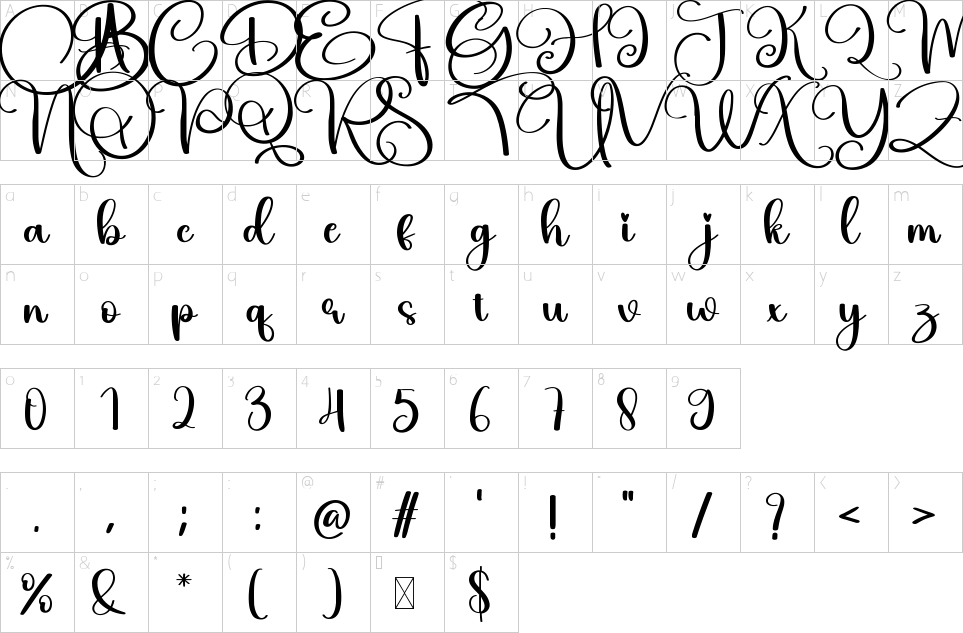
Anime Font é uma fonte animada e divertida, perfeita para aqueles que desejam dar um toque especial a seus projetos. Designada por scratchones, esta fonte foi projetada para aprimorar a experiência do design em ambientes Windows e Mac. Com uma aparência vibrante e animada, ela adicionará um toque especial e único aos textos em suas criações. Esta fonte já foi baixada 1,787 vezes, evidenciando o seu valor e popularidade entre criadores de design. Em uma categoria de fontes gratuitas, Anime Font não só oferece um design atraente, mas também uma opção de usar sem pagar.